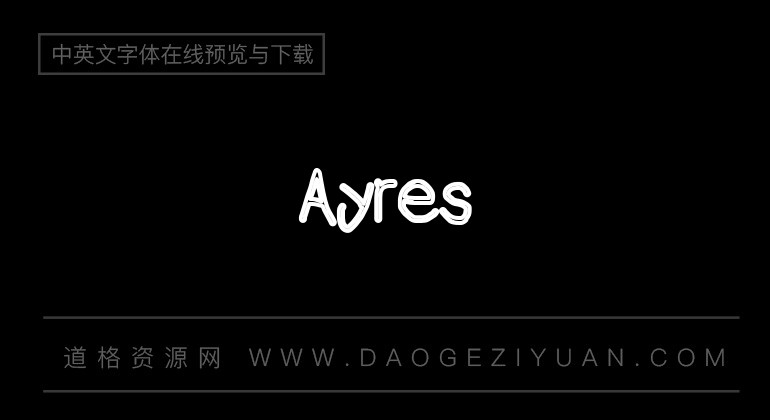
Ayres 字体是一种非常独特和优美的手写风格字体,由设计师 Dan Rhatigan 在2011年创建。这种字体的特点是具有类似手写字体的笔画和线条,但同时也保留了一定的规范性和松散的结构。Ayres 字体包含了丰富的字形,包括大小写字母、数字、标点符号等,因此可以用于各种场合,例如海报、广告、印刷品等。 Ayres 字体的字形流畅、舒展,同时又不失清晰度和可读性,使其在设计和排版领域备受欢迎。无论是用于商业用途还是个人用途, Ayres 字体都是一种非常优美和独特的选择。内容介绍
Ayres是一款非常不错的手写艺术字体,具有很好的视觉感,适合于文化类的宣传设计、商业类品牌的广告和产品包装设计以及个性化文字排版等较多场景。